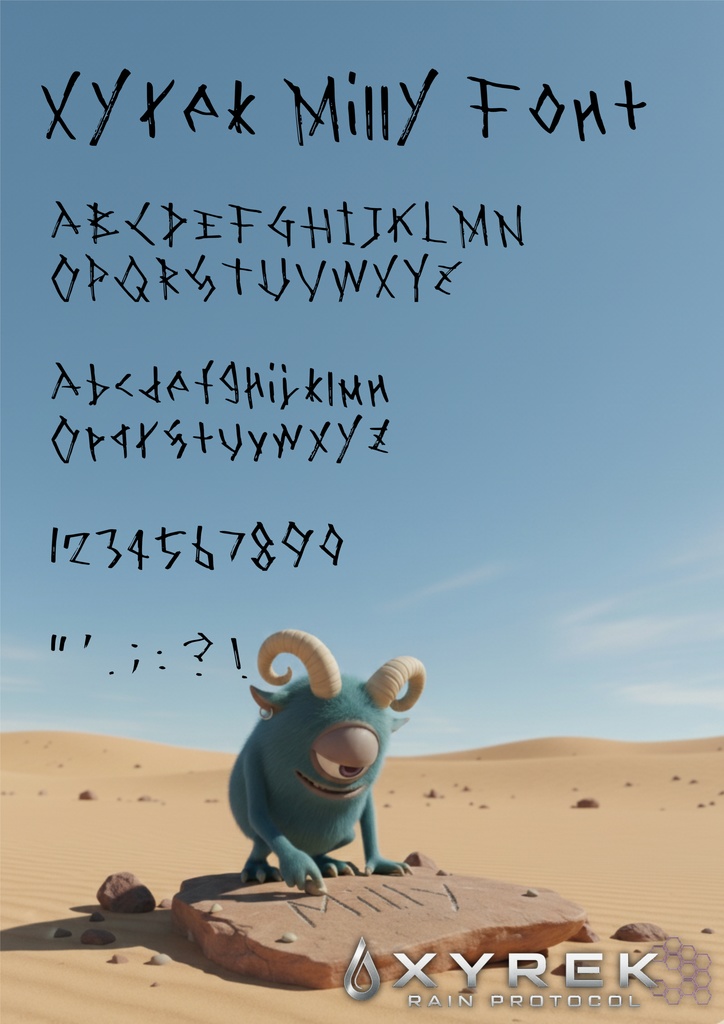
Xyrek Milly Font
自作SFアニメの登場キャラクターである Milly(ミリー)が、小石で岩に書いた文字🪨 という設定で、手書きで作ったフォントです。 ミリーは、まだ字が下手なうえに、適当な性格。 そのため、殴り書きで仕上げております😀 【フォント名】 Xyrek Milly Font 【内容物】 フォントファイル(.otf 及び .ttf) 利用規約テキスト(本内容と同じもの) 【利用規約】 本フォントをダウンロードした時点で、以下の規約に同意したものとみなします。 1. 利用可能範囲 本フォントは**個人利用(非営利目的)**に限り、自由にご利用いただけます。 イラスト、SNSのアイコン、個人的な動画、同人誌(営利を目的としないもの)などでの使用が可能です。 2. 禁止事項 商用利用の禁止: 収益が発生する広告、商品、ロゴ、印刷物、YouTube(収益化済み)等への使用は禁止します。 二次配布・転売の禁止: フォントファイルを他人に譲渡したり、別のサイトで再配布・販売したりすることを固く禁じます。 自作発言: このフォントのデザインを自分のものとして発表しないでください。 改変・公序良俗に反する使用: フォントの改変(アウトライン抽出後の加工を除く)や、犯罪、誹謗中傷、公序良俗に反するコンテンツでの使用を禁止します。 3. 著作権について 本フォントの著作権は制作者(Uka)に帰属します。 4. 免責事項 本フォントの使用により生じた損害やトラブルについて、制作者は一切の責任を負いません。自己責任でご利用ください。 ---------------------------------------- [Font Name] Xyrek Milly Font [Contents] Font files (.otf and .ttf) Terms of Use (this document) [Terms of Use] By downloading this font, you are deemed to have agreed to the following terms. 1. Grant of License This font is free to use for personal (non-commercial) purposes only. You may use it for illustrations, social media icons, personal videos, and fan publications (doujinshi) as long as they are not for profit. 2. Prohibited Matters No Commercial Use: Usage for revenue-generating advertisements, products, logos, printed materials, or monetized YouTube channels is strictly prohibited. No Redistribution or Resale: You may not transfer the font files to others or redistribute/sell them on other websites. No False Authorship: Do not claim the design of this font as your own. No Modification or Offensive Use: Modification of the font (except for processing after converting to outlines) and use in content that is criminal, defamatory, or contrary to public order and morals are prohibited. 3. Copyright The copyright of this font belongs to the creator (Uka). 4. Disclaimer The creator (Uka) shall not be held liable for any damages or troubles arising from the use of this font. Please use it at your own risk.